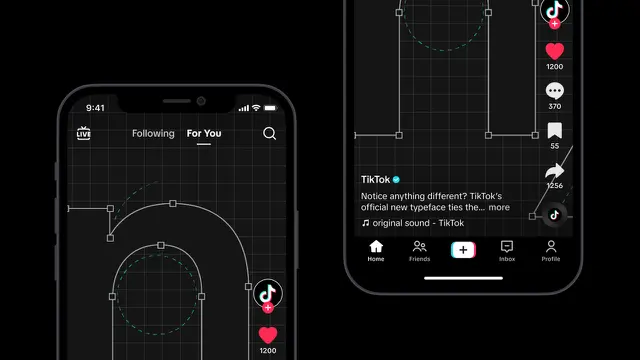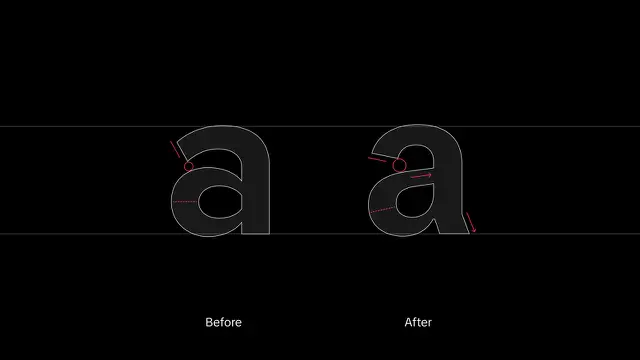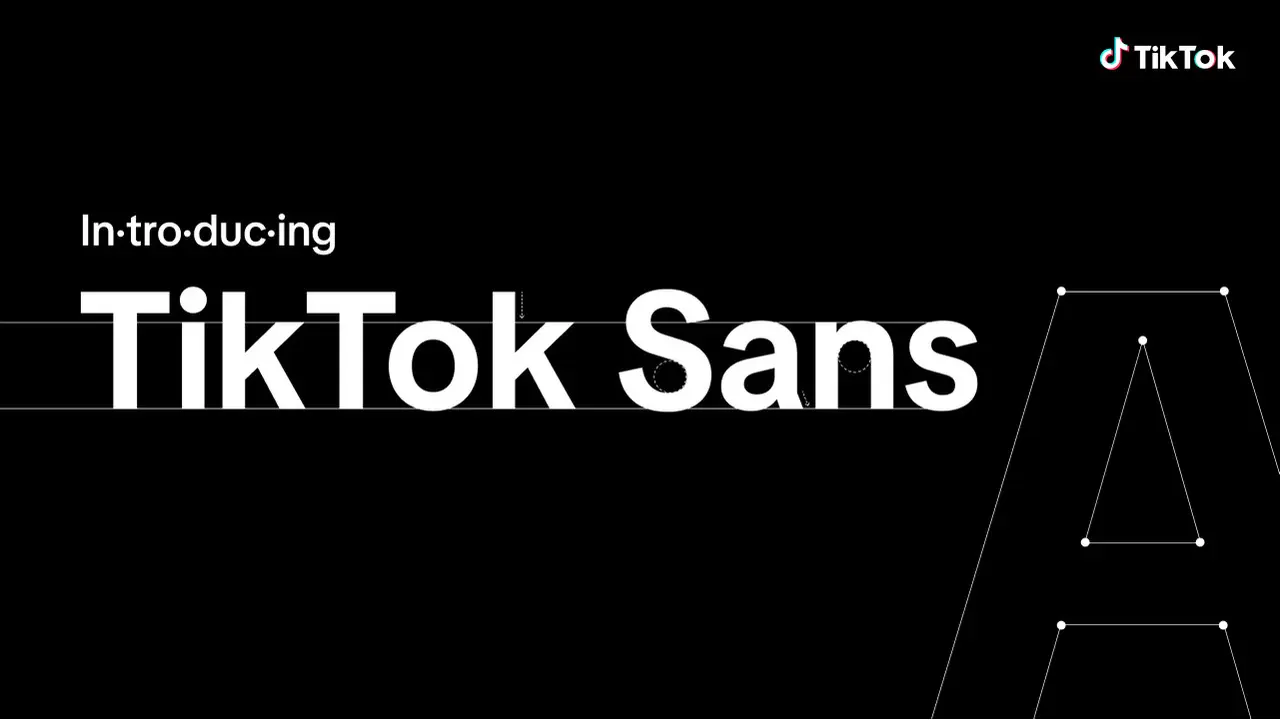
Liputan6.com, Jakarta - Beberapa hari lalu, TikTok meluncurkan font baru yang didesain khusus untuk aplikasi ini. Namun, perubahan ini menimbulkan keramaian, lantaran banyak pengguna yang tidak menyukai tampilan font baru tersebut.
Font baru bernama TikTok Sans ini menggantikan Proxima Nova dan dioptimalkan untuk meningkatkan kemampuan keterbacaan.
Berdasarkan postingan blog resminya, perusahaan mengatakan bahwa TikTok Sans memiliki bukaan yang lebih besar dan goresan yang lebih jelas. Hal ini membuatnya semakin mudah untuk dibedakan satu sama lain.
“Bentuk yang lebih licin dan sederhana, memungkinkan pengenalan dan keandalan yang lebih baik di seluruh bahasa,” ujar TikTok sebagaimana dikutip dari blog resminya, Selasa (23/5/2023).
Selain itu, tinggi garis font secara keseluruhan telah ditingkatkan dan berukuran sedikit lebih besar. Font baru ini akan terlebih dahulu tersedia dalam bahasa Inggris, Spanyol, Portugis, Prancis, Jerman, Italia, Indonesia, Turki, dan Vietnam.
Meski masih terbatas, TikTok berencana untuk menambahkan lebih banyak bahasa di masa mendatang.
Dalam mendesain font baru TikTok, perusahaan bergabung dengan banyak perusahaan teknologi.
“Dirancang untuk mencerminkan komunitas pencipta, visioner, dan pendongeng kami yang beragam, TikTok Sans melengkapi kepribadian platform kami--dari akar kami dalam hiburan hingga inklusivitas dan ekspresi diri," kata perusahaan dalam blognya.
Lalu mengapa kebanyakan pengguna TikTok mengeluhkan dan kurang menyukai tampilan font baru ini? Apakah font dapat dikembalikan ke bentuk semula atau diubah secara manual?
Reaksi Pengguna Terhadap Font Baru TikTok
Font baru TikTok tampak lebih tinggi dan ramping, dengan jarak yang sedikit lebih rapat dari sebelumnya.
Perubahan ini sebenarnya tidak terlalu signifikan sehingga beberapa pengguna mungkin belum menyadarinya. Namun, tidak sedikit pengguna yang tidak senang dengan pembaruan ini.
Sejak perubahan tersebut, pengguna platform ini telah mengungkapkan berbagai reaksinya secara online, baik melalui video pendek yang diunggah di TikTok atau cuitan di Twitter.
“Bagusan yang duluuuu,” komentar akun @itu.m**** di sebuah postingan TikTok.
“Kaya aplikasi jadul sekarang,” timpal akun @dil*****.
“Bedanya di mana sih? gatau soalnya,” tulis akun @indahc*******.
Meskipun banyak yang tidak suka, terdapat pula sejumlah pengguna yang justru memuji font baru tersebut.
“Bagusan yang ini loh padahal,” komentar akun @leun****.
Bisakah Font TikTok Diubah ke Tampilan Semula?
Dilansir ScreenRant, Selasa (23/5/2023), perubahan font tersebut tampaknya memengaruhi semua area aplikasi, mulai dari komentar hingga teks video dan judul halaman feed.
Sayangnya, saat ini aplikasi tidak memiliki pengaturan atau menyediakan cara untuk mengubah font bagi mereka yang ingin kembali ke font klasik.
Kendati demikian, seperti kebanyakan perubahan di aplikasi lainnya, kemungkinan besar pengguna akan terganggu selama beberapa waktu. Ketika sudah sering memakai aplikasi secara normal, pengguna akan terbiasa dengan font baru tersebut.
Tetapi karena perubahan yang dilakukan pada font sangat kecil, pengguna mungkin tidak menyadari bahwa telah memiliki font baru tersebut.